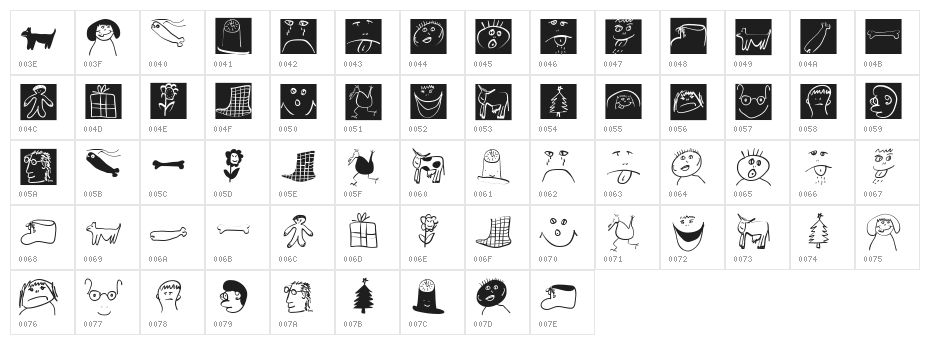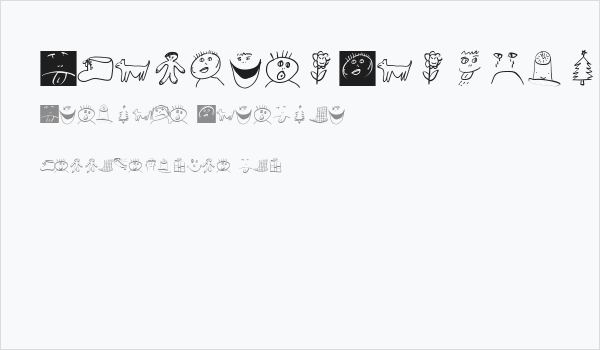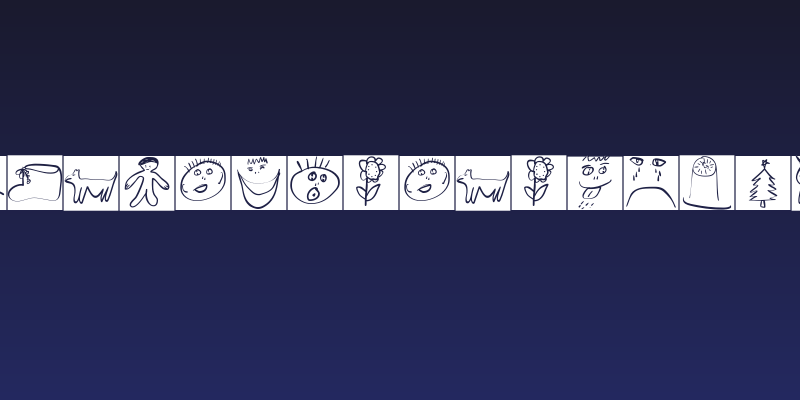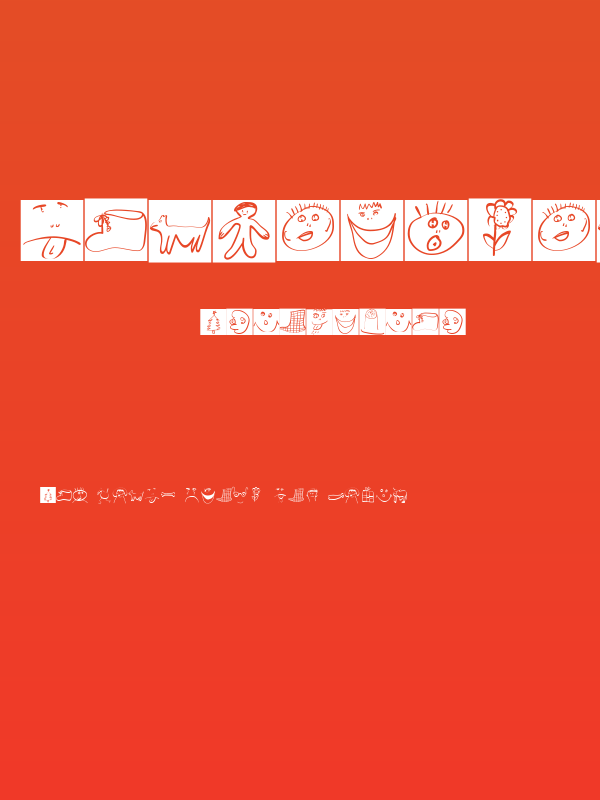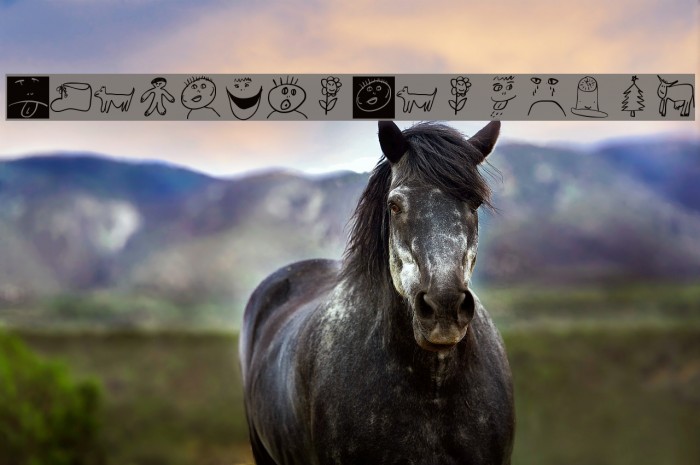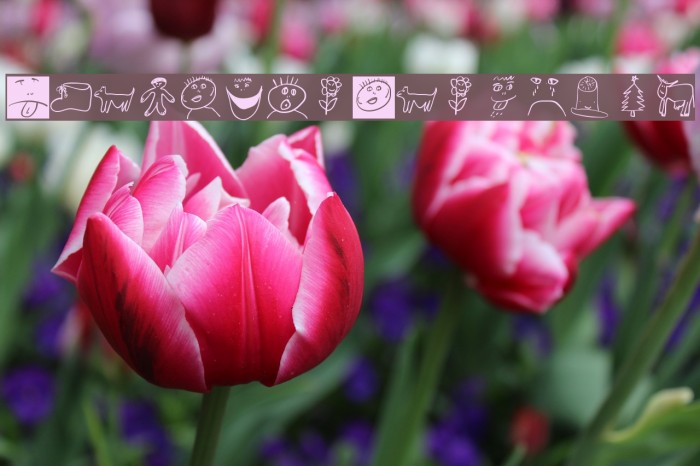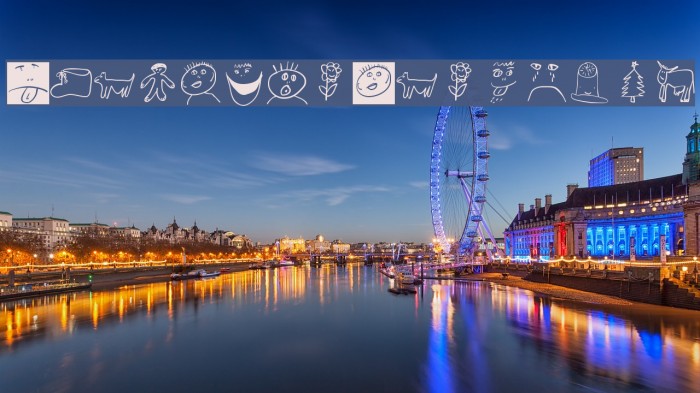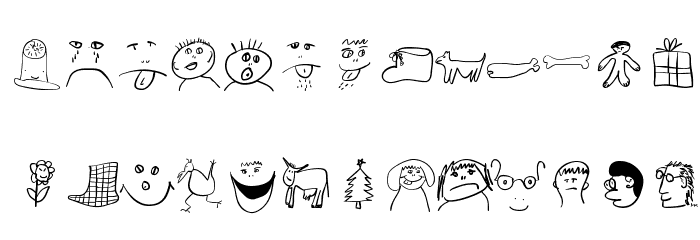
ChildrenDingbats Font
| Stile generale | Playful, Whimsical |
| Caso d'uso | Decorative elements, Illustrations |
| Progetti proposti | Ideal for children's books, educational materials, playful branding, and creative art projects. |